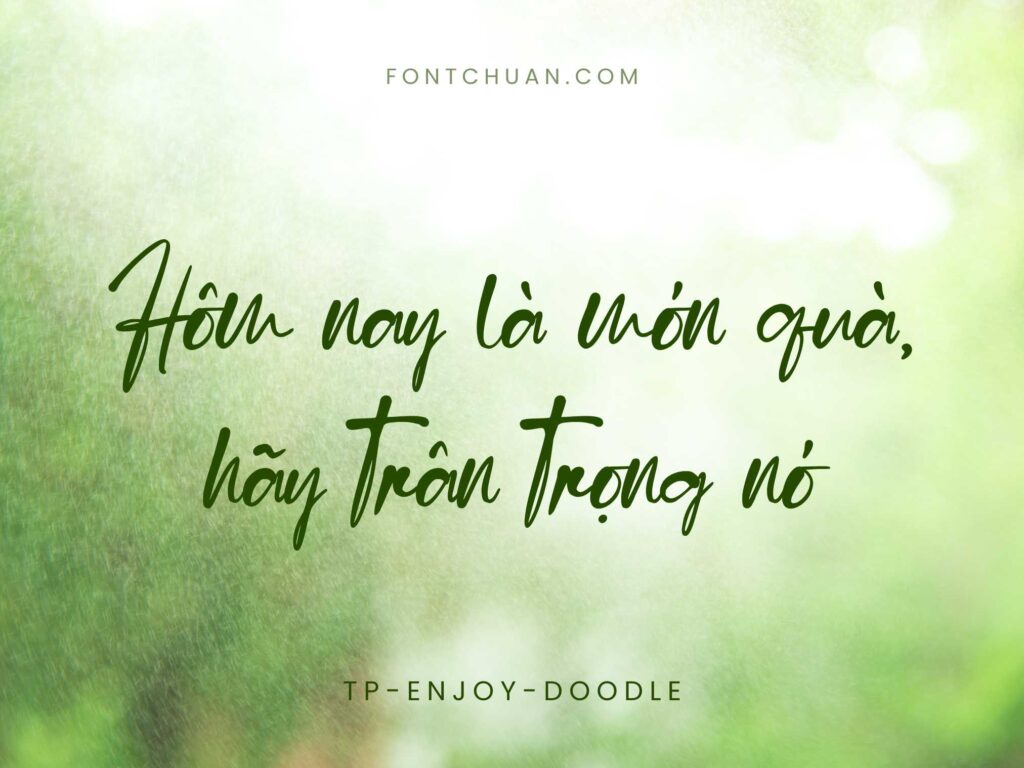
Font TP Enjoy Doodle Regular Việt Hóa
Enjoy Doodle là một font chữ viết tay được thiết kế bởi Natha Studio, mang lại cảm giác ấm áp và thân thiện. Các chữ cái được thiết kế giống như chữ viết tay nối liền, tạo nên sự tự nhiên và mượt mà trong từng nét chữ. Font này đã được Việt hóa để hỗ trợ tiếng Việt bởi Tuỳn Pucca, đồng thời hỗ trợ nhiều ngôn ngữ khác, giúp mở rộng phạm vi sử dụng trên toàn cầu. Font này được sưu tầm và chia sẻ bởi thành viên của Font Chuẩn, đáp ứng nhu cầu của người dùng và ứng dụng thực tế vào các dự án thiết kế.
Đặc điểm thiết kế của Enjoy Doodle bao gồm các đường nét uyển chuyển và tinh tế, tạo cảm giác gần gũi và thân thiện. Font này phù hợp cho các ứng dụng như tiêu đề, logo, thiệp mời và các dự án sáng tạo khác. Các ngành nghề phù hợp bao gồm quảng cáo, giáo dục và thiết kế đồ họa.